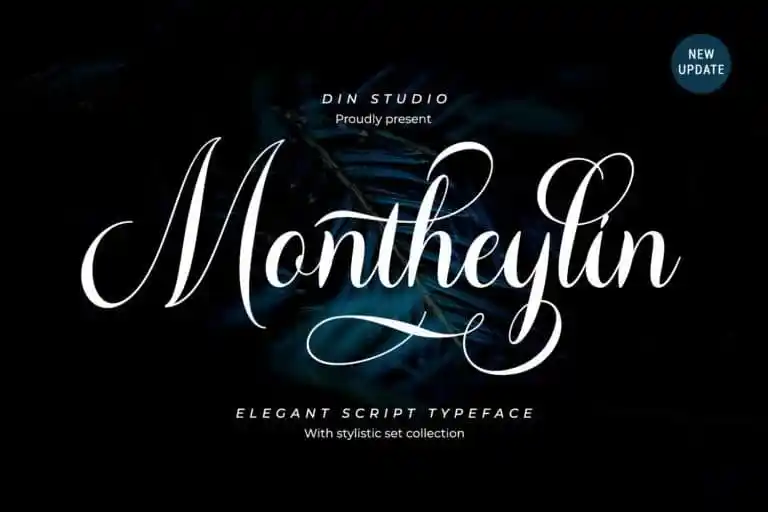
Montheylin Calligraphy Font – Download Grátis
A fonte ‘Montheylin Calligraphy Font’ é uma escolha perfeita para quem busca criar designs originais e modernos. Foi projetada por 99designs, ideal para projetos profissionais, desde as marcas de marca até os anúncios e mensagens únicas como cartões de casamento e citações. A fonte é tão versátil quanto divertida, com uma aparência elegante e contemporânea que pode transformar qualquer design em um hit. Seja para criar marcas memoráveis ou textos emotivos, essa fonte criativa será a sua melhor aliada. Sem dúvida, ela fará você se surpreender com as infinitas possibilidades criativas quando usar ‘Montheylin Calligraphy Font’.